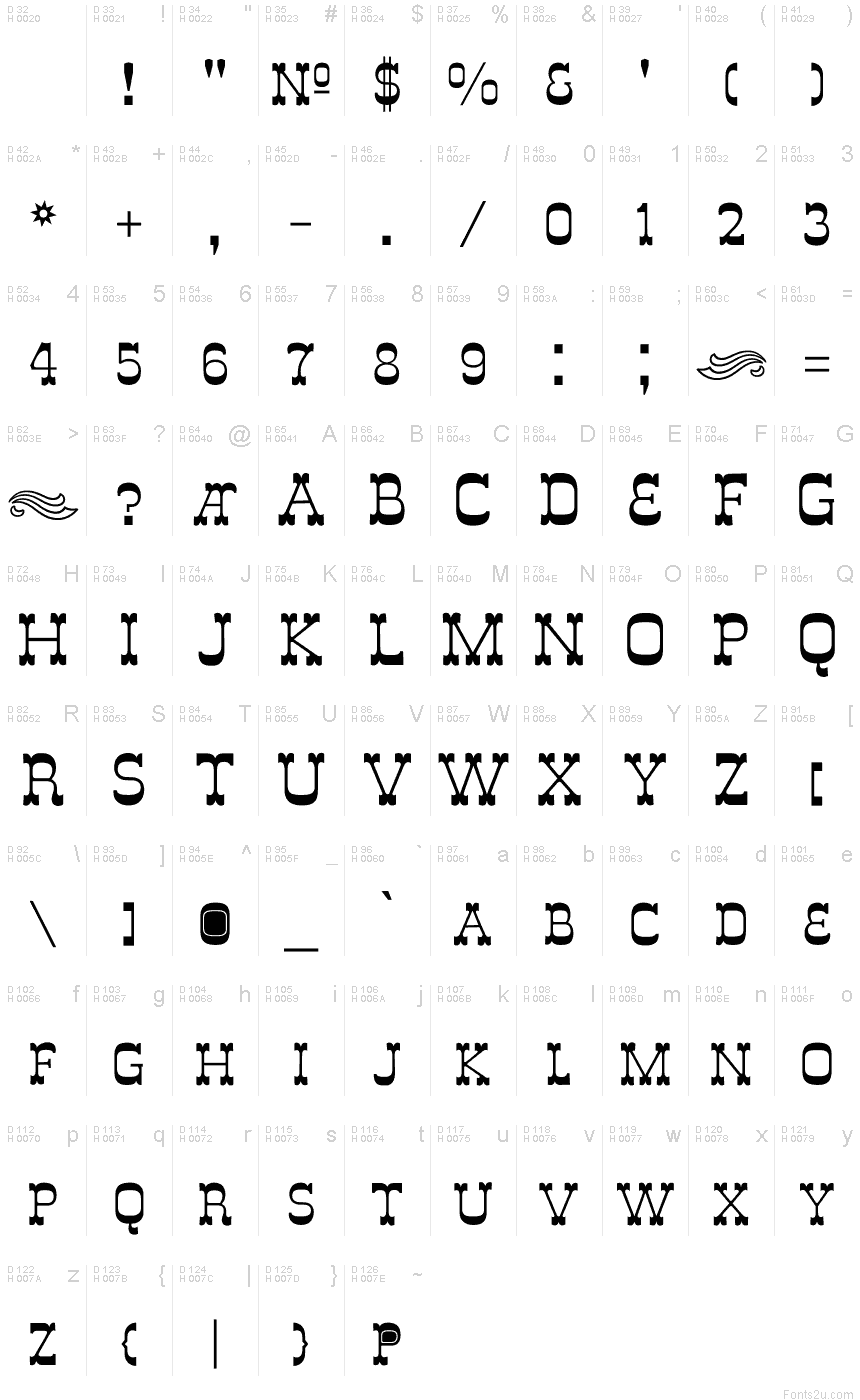
DeLouisville SmallCaps od Jamese Arboghasta – S E N T I N E L T Y P E je bezplatné westernové titulkové písmo z rodiny DeLouisville. Díky robustním patkám, těsným křivkám a rytmu malých kapitálek působí jako nápisy přímo ze starého nádraží nebo dveří salónu. Písmena jsou kompaktní a výrazná, s masivními svislými tahy a hranatými rameny, která připomínají otisk dřevěného razítka – na stránce působí silně, tmavě a lehce dramaticky.
DeLouisville SmallCaps zazáří na plakátech rodea, etiketách řemeslné whiskey, jídelních lístcích barbecue, vintage logách, tematické grafice i jako výrazný nadpis. Konzistentní struktura kapitálek zajišťuje čitelnost delších slov, zatímco si písmo zachovává dekorativní a drsný ráz. Zkuste DeLouisville SmallCaps zkombinovat s čistým geometrickým bezpatkovým písmem a nastavte toto westernové písmo o něco větší s velkorysými rozestupy, aby vynikly jeho detailní tvary.
DE LOUISVILLE tuscan, from S E N T I N E L T Y P E designed by James Arboghast
Relive the spirit of 19th century America in whimsical upbeat style with De Louisville tuscan. Echoing the Victorian craze for lavish decoration, De Louisville captures the antique flavor of a music parlor with refreshing cartoon ambiance. Cute, bubbly curves evoke strawberries & cream, a frothy head of beer, or the lace trimmings of a fine young lady's skirt, in a light-hearted display face designed for contemporary use.
De Louisville is ideal for confectionary, 19th century Americana, toys & feminine subjects.
The De Louisville set features: